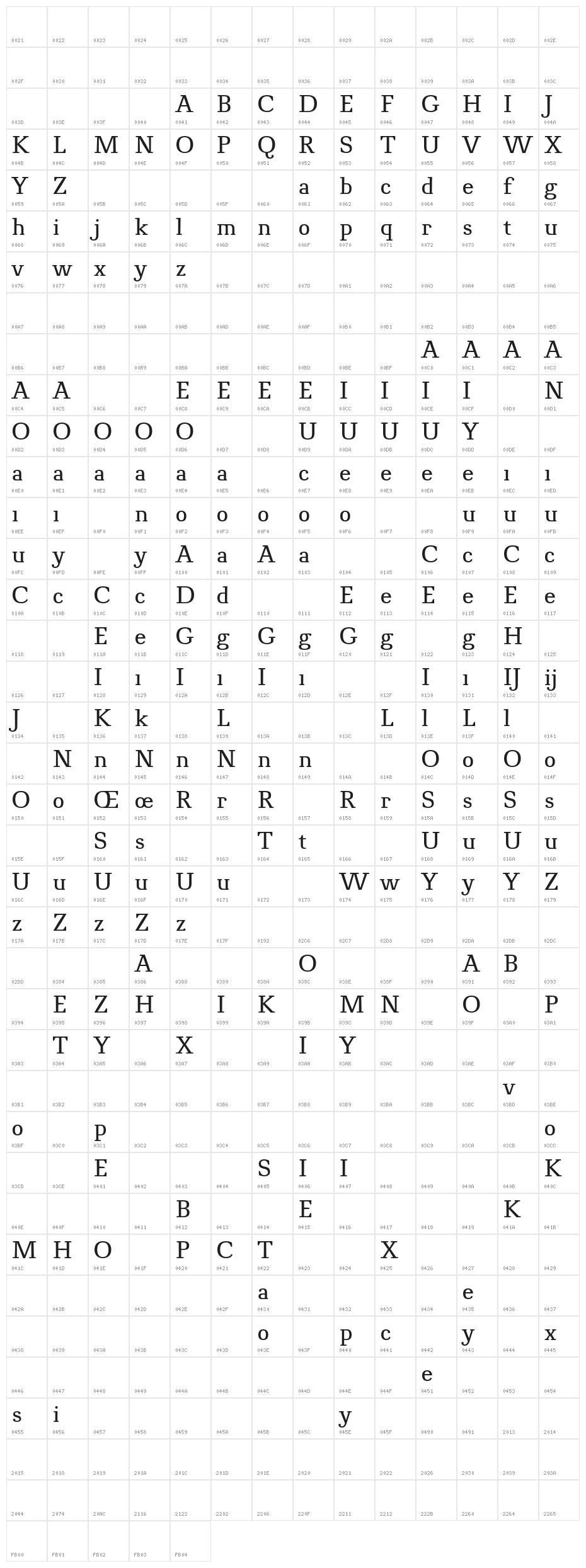
NovelloPro Font
✎ Serif
| Kategorien | Serif |
| Gesamtstil | Classic |
| Anwendungsfall | Headlines, Body text, Logos |
| Vorgeschlagene Projekte | Ideal for editorial design, book covers, formal invitations, and branding projects that require a touch of elegance. |